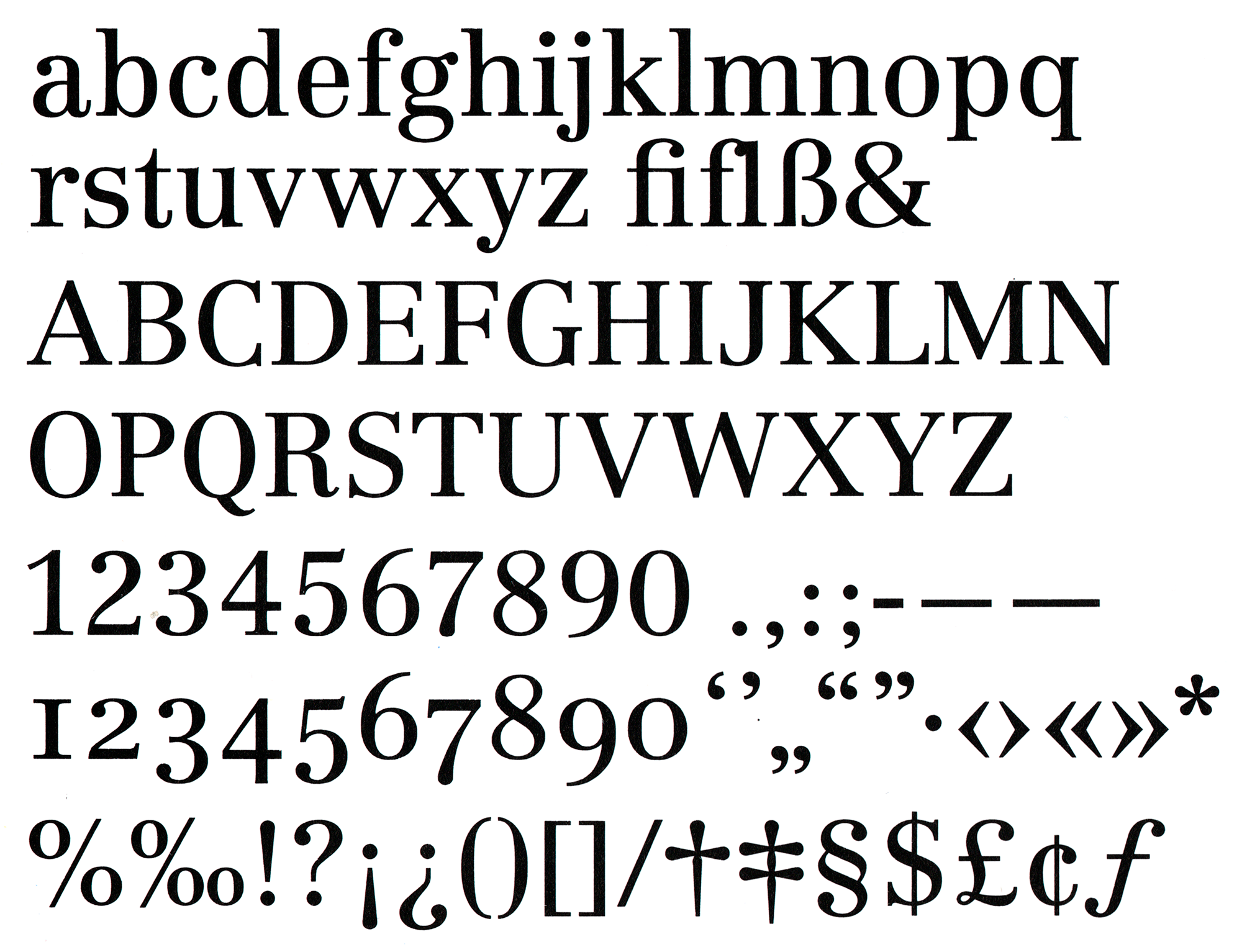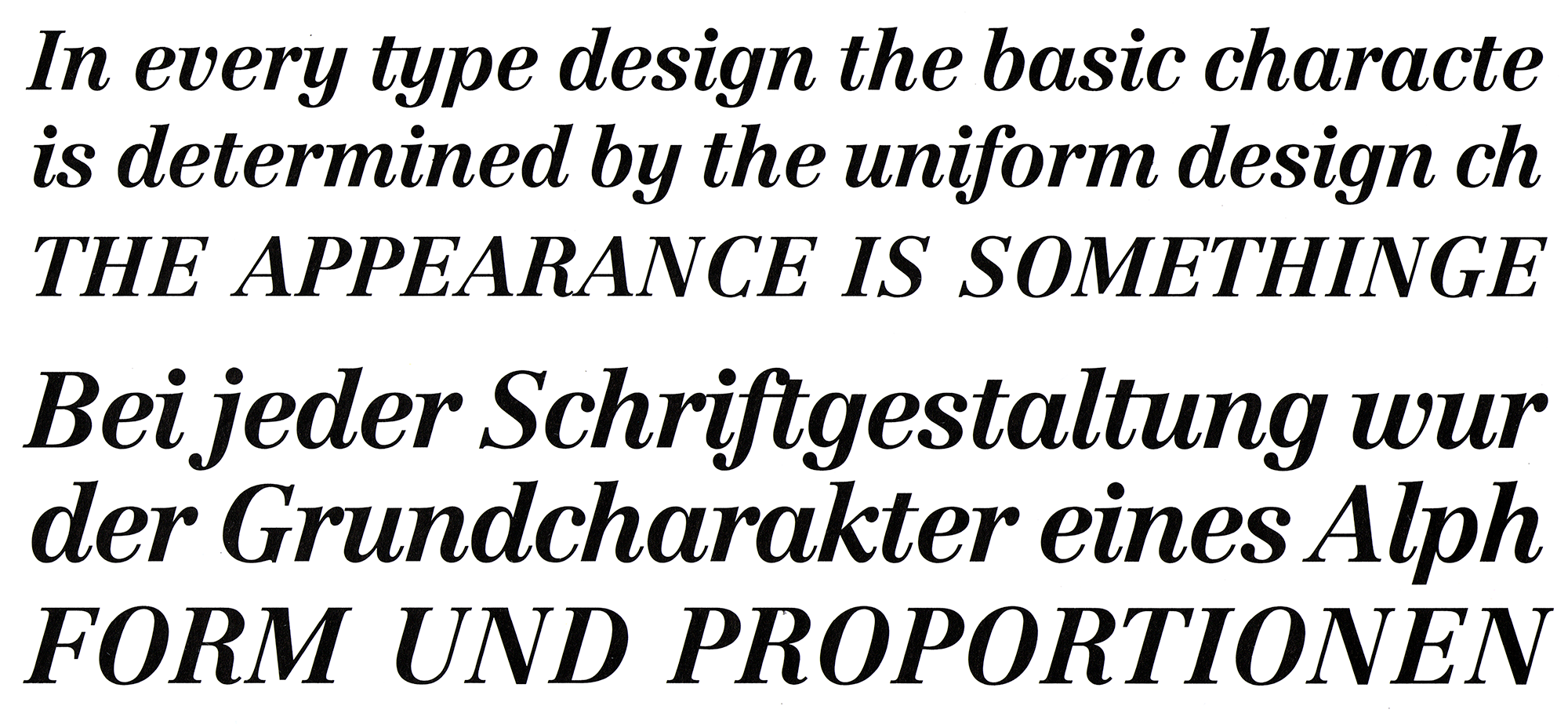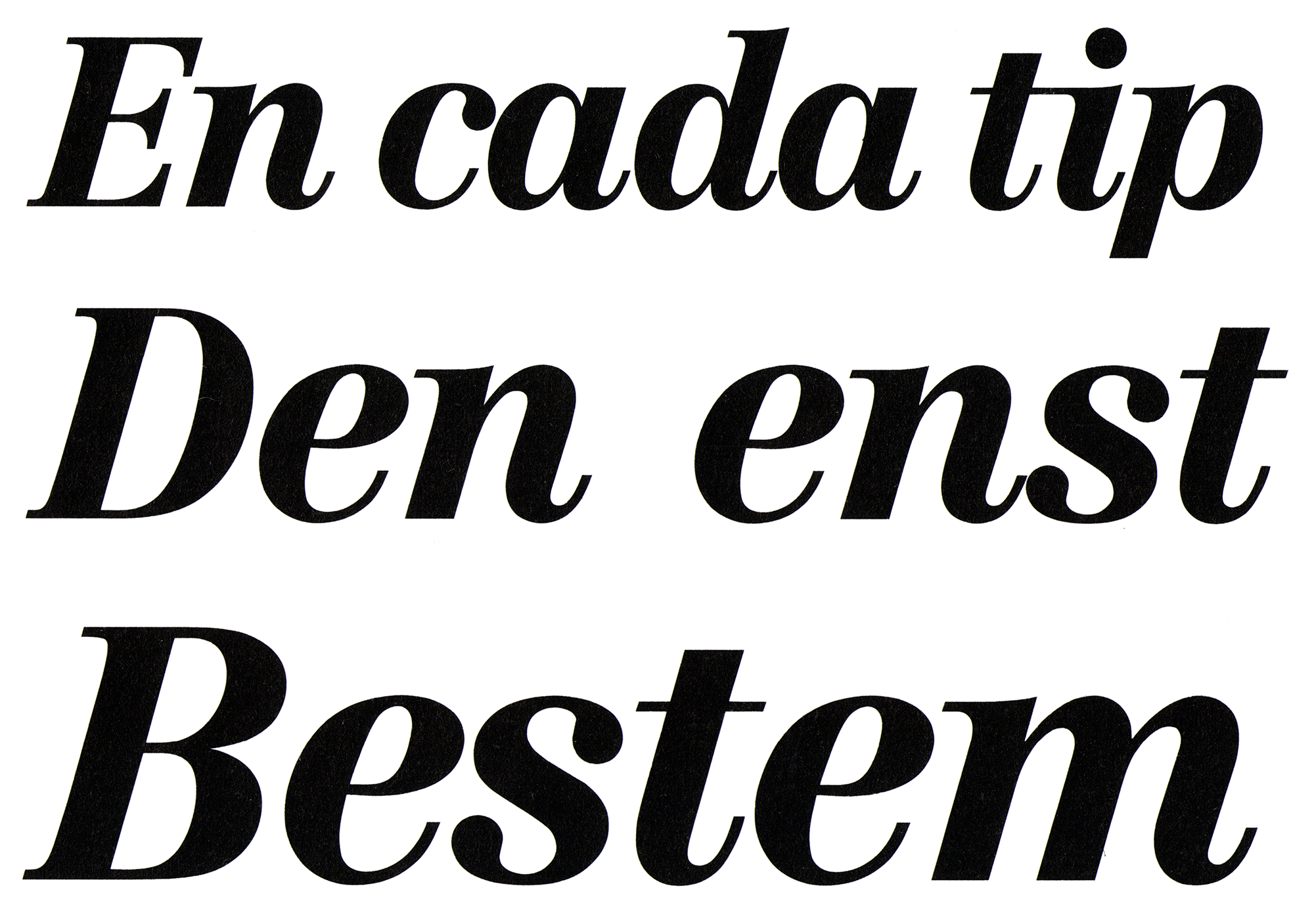
• 1986
• Serifen:
• serif
• Antiqua statisch
Die Linotype Centennial ist eine Antiqua-Werkschrift von Adrian Frutiger und erschien 1986 zum Jubiläum 100 Jahre Linotype als Fotosatzschrift. Zur Familie gehören vier Strichstärken mit Kursiven.
Die Schrift ist heute in einer Pro-Version mit erweiterter lateinischer Belegung mit Kapitälchen verfügbar.